Букви графіті і шрифти
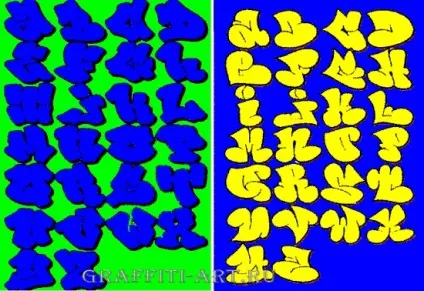
Багато райтери мають свій стиль і придумують самостійно літери графіті. Але все одно існують основні принципи і шрифти, якими користується більшість.
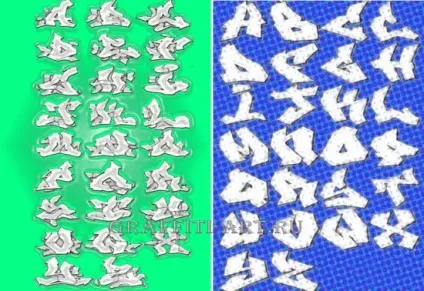
Я теж іноді вигадую свої букви і замальовую їх на папері, по-перше, щоб не забути, а по-друге, відтворювати на стіні знайомий шрифт потім легше, ніж винаходити щось на ходу.
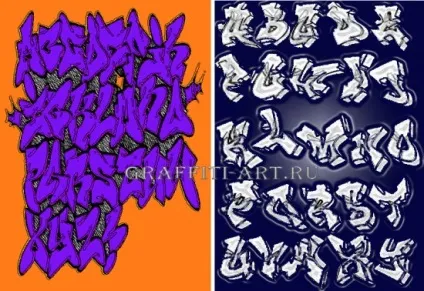
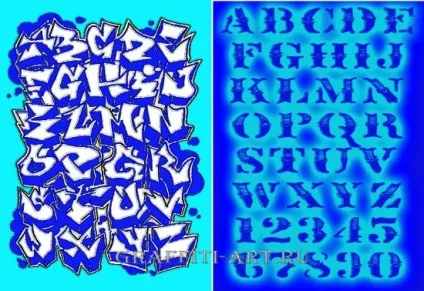
Найпоширеніші стилі написання і букви графіті
Такі мультяшні об'ємні букви - найпоширеніший варіант. У шрифті баббл букви повинні зливатися і як би насуватися один на одного. Єдиний мінус - іноді прочитати, що написано в цьому стилі досить важко, так як літери можуть спотворюватися практично до невпізнання.
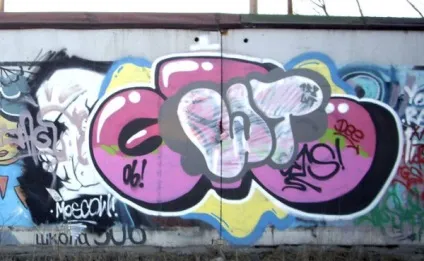
Блокбастерс
Для цього стилю графіті потрібно спочатку нанести на поверхню тон. Краще зробити це за допомогою валика, але можна і балоном. Це робота не для одного і краще виконувати її разом з товаришами. На фон наносяться рівні й чіткі літери графіті. Багато райтери використовують блокбастерс як свій фірмовий стиль.
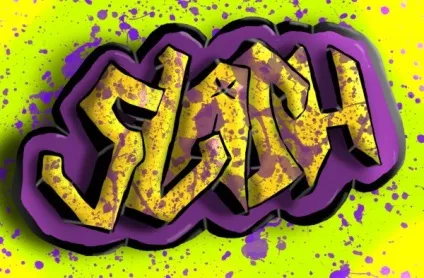
Вайлд
Об'ємний графіті стиль і досить складний. Букви в даному випадку вимагають ретельного опрацювання. Не раджу новачкам намагатися починати з нього. Все одно нічого путнього не вийде.
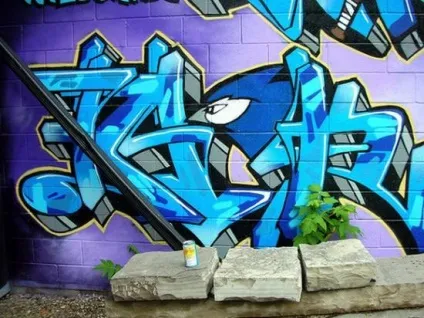
Месія
Ці графіті літери придумали в Америці. Багатошаровий шрифт з ефектом накладення зображень. Теж не найлегший варіант, який використовують досить досвідчені райтери. Такі букви графіті не намалюєш за 15 хвилин.
характер
Це вже навіть не букви, а ціла картина. Намалювати її можна тільки при наявності різних насадок. Зазвичай в характері зображують героїв коміксів.
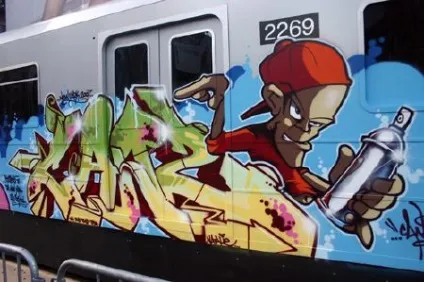
Throw up
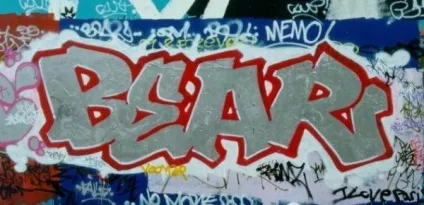
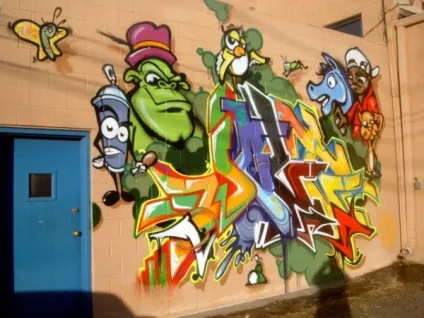
Я малюю досить давно і починав як і більшість. Тупо брав шрифт з инета і перірісовивал в зошит. Але хочу дати пораду: Ви можете користуватися алфавітами з інету. АЛЕ! Намагайтеся додати чогось свого перетворіть шрифт добавте вигинів, ліній, з'єднайте їх і буде набагато краще вже повірте мені на моєму особистому досвіді випробувано.